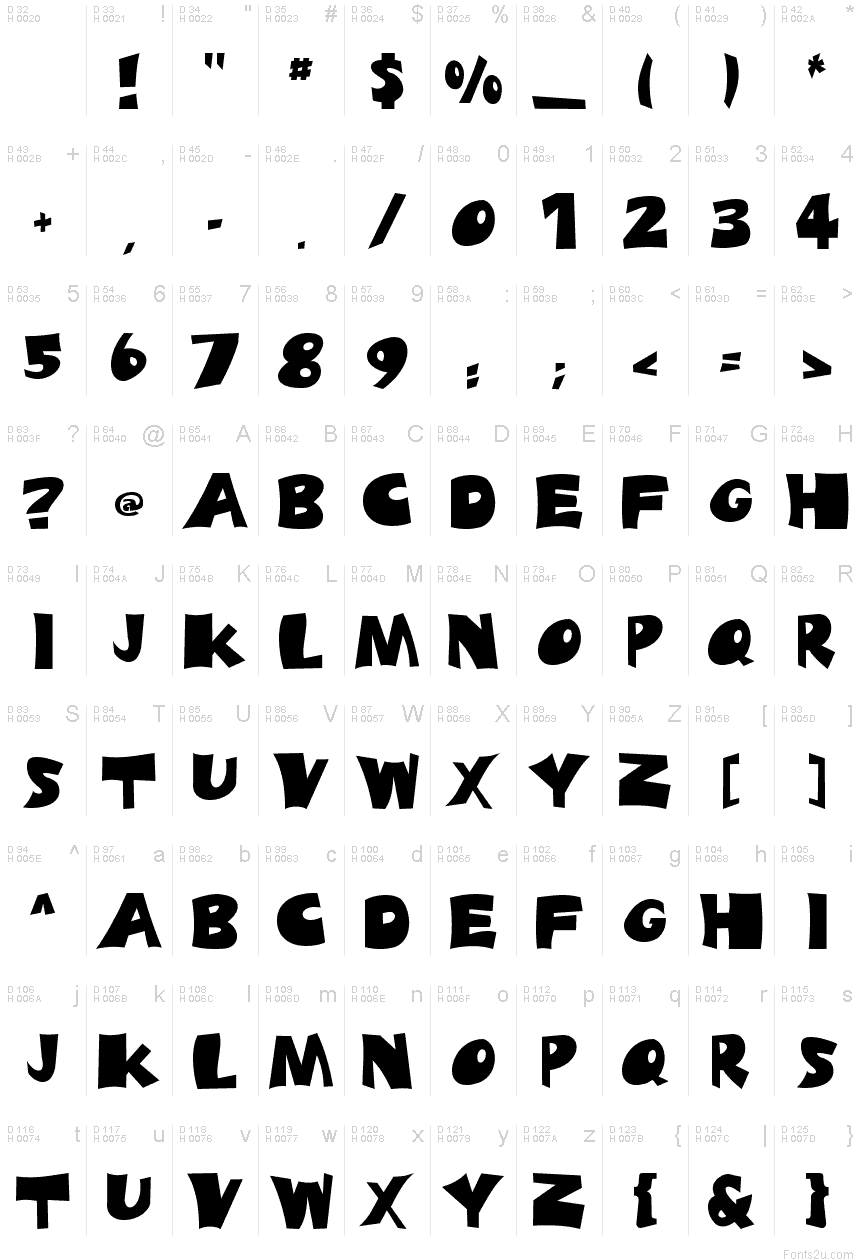
Big Truck od Cosmi to darmowy, komiksowy krój pisma z dużymi, skocznymi literami, które wyglądają, jakby zostały wycięte z grubego, zamoczonego w tuszu papieru. Wyraziste kreski, krzywe kąty i ciasne odstępy nadają mu hałaśliwą, pełną energii formę, która dosłownie wyskakuje z ekranu – przypominając napisy na pudełku z zabawkami lub tytuły porannych kreskówek. Całość sprawia wrażenie ręcznie rysowanej i nieco nieokiełznanej, dzięki czemu jest zabawna, a nie sztywna czy korporacyjna.
Dzięki Big Truck Twoje nagłówki staną się natychmiast głośniejsze i bardziej figlarne – świetnie sprawdzą się na okładkach książek dla dzieci, opakowaniach zabawek, zaproszeniach urodzinowych, zabawnych plakatach, szkolnych ulotkach czy miniaturach na YouTube. Ten darmowy font najlepiej sprawdza się w dużych rozmiarach, gdzie jego nieregularne krzywe i duża waga naprawdę przyciągają wzrok. Połącz go z czystym, lekkim krojem bezszeryfowym w tekście uzupełniającym, aby zachować czytelność, podczas gdy Big Truck zajmie się przykuwaniem uwagi.